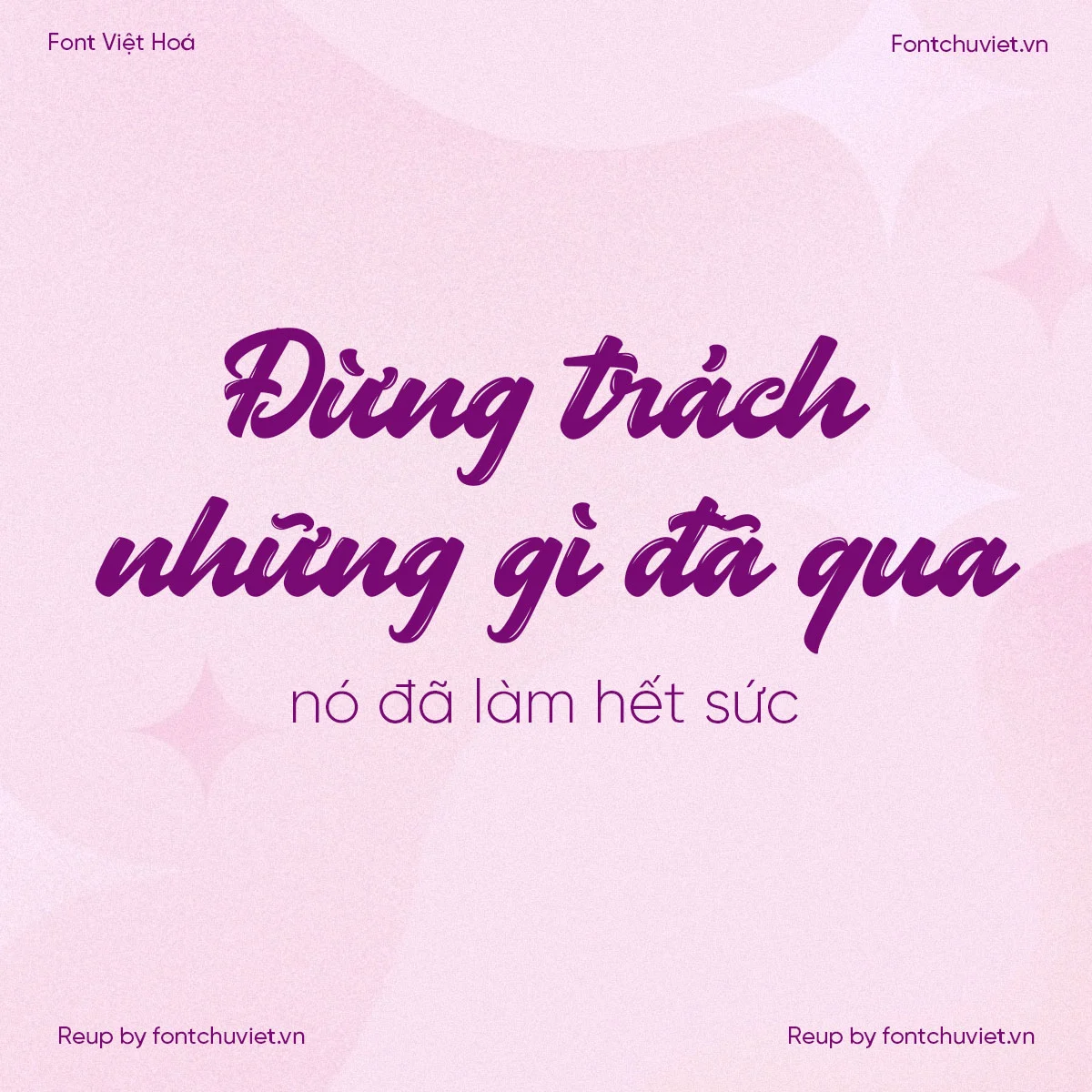
Font VL Austten – Font Việt hoá
Cỡ chữ: 60px Aa aa AA Thử font Việt hoá 1234567890 0/300 Gõ văn bản bên dưới để xem trước font chữ ◪ View Glyphs Font VL Austten – Font Việt hoá là một font chữ đậm, dạng brush tạo cảm giác nổi bật khi sử dụng. Tuy nhiên, nhiều người vẫn chưa hiểu rõ … Đọc tiếp Font VL Austten – Font Việt hoá